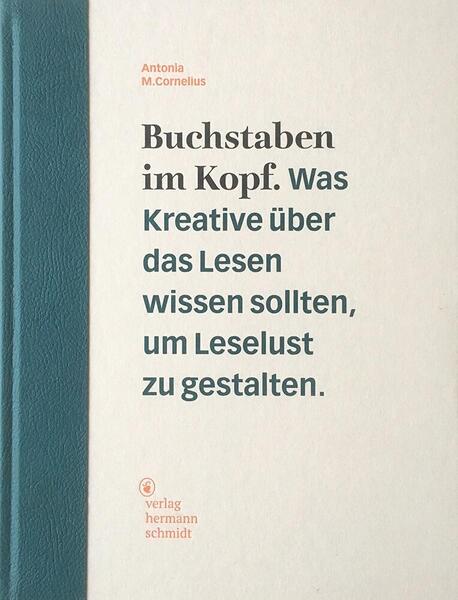
Antonia Cornelius studierte Kommunikationsdesign an der HAW Hamburg. Als Abschlussarbeit ihres Bachelor-of-Arts-Studiums entstand 2015 im Bereich Typedesign bei Prof. Jovica Veljović das Buch »Schrift lesbar gestalten. Ein Leitfaden für Textschriften«. 2017 erschien dieses Werk in einer überarbeiteten Fassung mit dem Titel »Buchstaben im Kopf – Was Kreative über das Lesen wissen sollten, um Leselust zu gestalten« beim Verlag Hermann Schmidt.
Die 180 Seiten, die durchgehend in drei Sonderfarben gedruckt sind, gliedern sich in vier Kapitel. Die ersten 30 Seiten liefern typografisches Grundlagenwissen. Es folgen circa 50 Seiten zum Thema Lesen. Wie wir sehen, lesen, Buchstaben und Wörter erkennen und so weiter. Hier wird sich auf die internationale Lesbarkeitsforschung der letzten Jahre bezogen und die Ergebnisse werden anschaulich dargestellt. Es folgen weitere 50 Seiten zum Thema Entwerfen von Schrift. Wie setzen sich Schriftfamilien zusammen? Wie gestaltet man sie und wie optimiert man die Leserlichkeit und Lesbarkeit? Den Abschluss bildet das Kapitel »Anwenden«. Hier wird in einem Überblick auf die wesentliche Kriterien und Parameter der Mikro- und Makrotypografie eingegangen.
An der technischen und gestalterischen Ausstattung des »Schmidt-Buches« gibt es wie so oft nichts auszusetzen. Und der lockere anschauliche Schreibstil gefällt genauso wie die Tatsache, dass das Buch inhaltlich auf der Höhe der Zeit ist. OpenType, Variable Fonts, InDesign-Kerning, Textarten nach der neuen DIN 1450 – das Buch passt perfekt in die heute digitale Typografie. Die leicht verständliche Zusammenfassung der Lesbarkeitsforschung dürfte in dieser Form und in deutscher Sprache bislang einmalig sein und fand sich in den letzen Jahren nur in englischsprachigen Büchern wie etwa Sofie Beiers Reading Letters.
Beim ersten Lesen wunderte ich mich allerdings stellenweise, an wen genau sich die Autorin richtet. Dies klärte sich für mich erst im Anhang auf. Die Autorin arbeitet an einer eigenen Schrift: der Legilux und das Buch dokumentiert somit die eigene Lesbarkeitsforschung aus Sicht des Typedesigners, wie es der Originaltitel der Universitätsabschlussarbeit auch noch aufzeigt. Wenn sich der Schmidt-Titel jetzt an alle »Kreative« widmet, ist das vielleicht etwas zu weit aufgemacht. So manches Detail im Buch – insbesondere im Kapitel »Entwerfen« – richtet sich klar nur an Schriftgestalter. Direkt empfehlen würde ich das Buch daher eher für Leser in der gleichen Situation wie die Autorin, also angehende Schriftgestalter, die sich einen Überblick über die entsprechenden Grundlagen verschaffen wollen. Andere typografische Einsteiger, die sich für reine Schriftanwendung interessieren, können aber in den anderen Kapiteln freilich auch nützliche Informationen finden.
Untertitel: Was Kreative über das Lesen wissen sollten, um Leselust zu gestalten